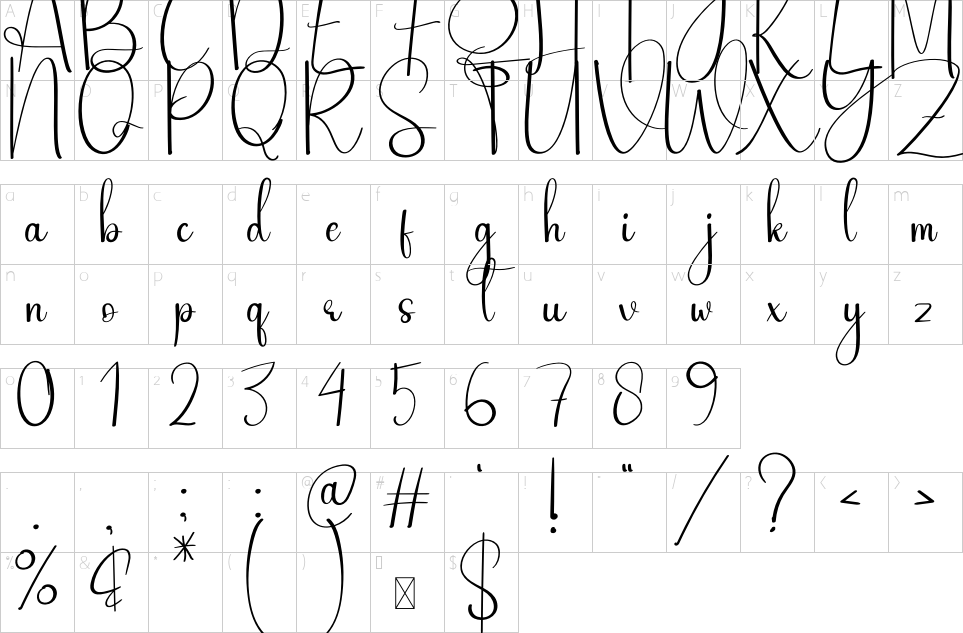
A fonte ‘Saturday Font’ é uma elegante escolha para adicionar um toque de diversão a suas produções digitais. Desenhada por ninguém menos que William Jhordy, esta fonte é uma delícia para os olhos. Se você está buscando uma maneira simples e sofisticada de dar um toque pessoal a suas criações, ‘Saturday Font’ é uma excelente escolha. Desenvolvida para ser facilmente usada tanto em dispositivos Windows quanto em Mac, esta fonte é uma ótima opção para aqueles que buscam uma fonte de qualidade que ainda é totalmente gratuita. Com mais de 1.196 downloads, é evidente que os criadores de design encontraram algo especial em ‘Saturday Font’, e agora você também pode experimentar a beleza desta fonte única.